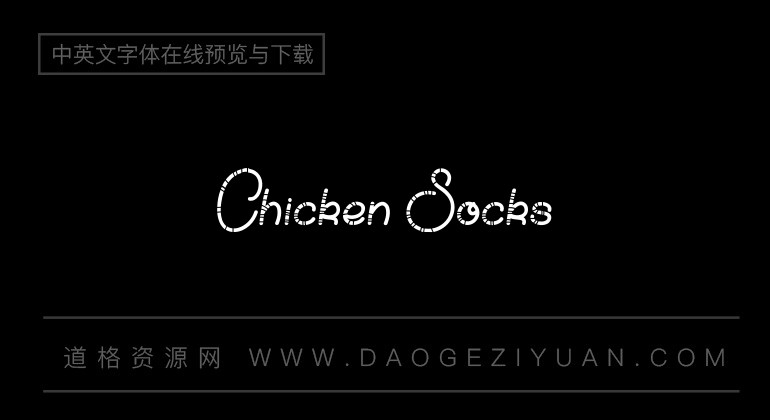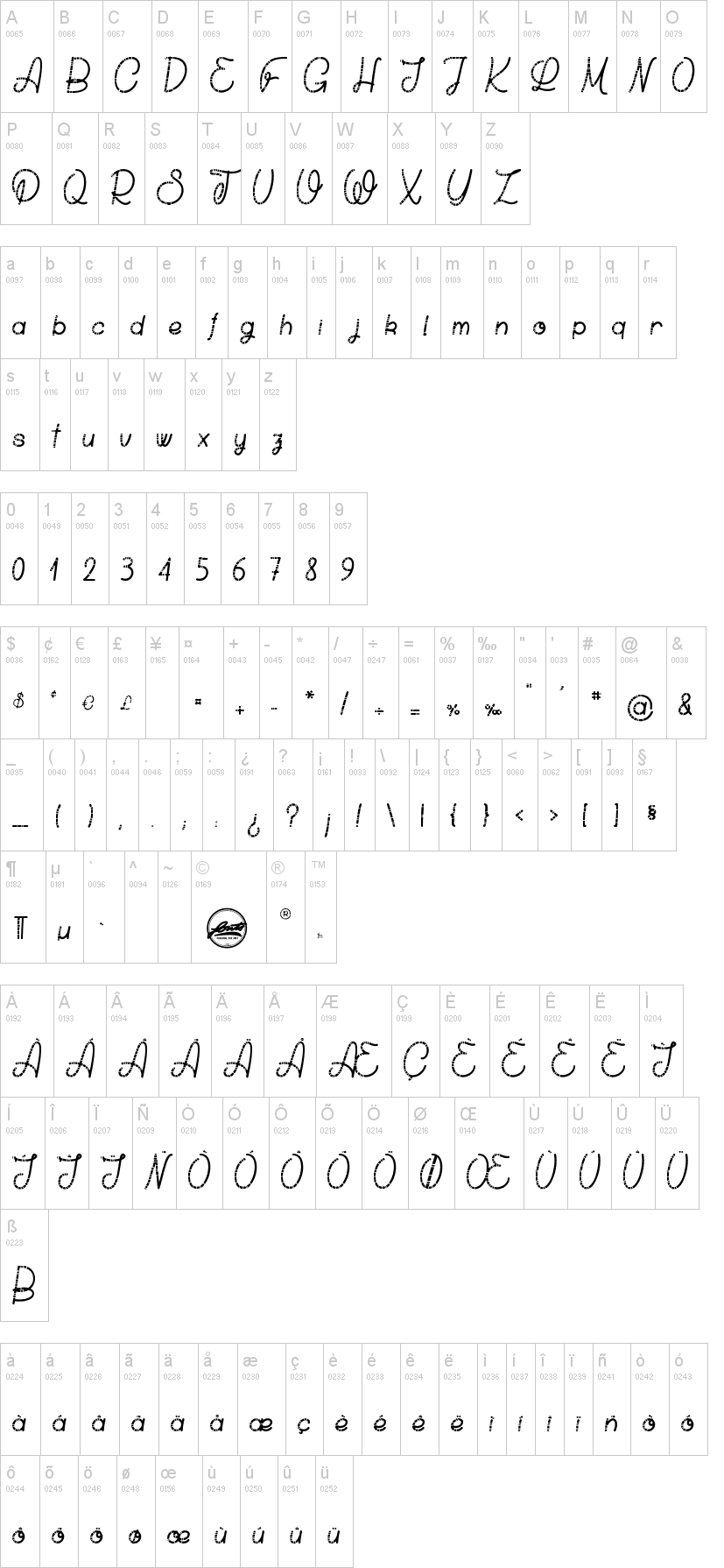
Chicken Socks 字体是一款由英国设计师Liam Smith创作的手写类字体。它的特点是极具特色的萌萌哒的笔画,清新活泼,既可以用于商业设计,也可以用于个人设计,如文字排版、漫画、海报等。它有着独特的风格,能够更好地表达出个性化的设计感。内容介绍
Chicken Socks是一款非常不错的手写艺术字体,具有很好的视觉感,适合于文化类的宣传设计、商业类品牌的广告和产品包装设计以及个性化文字排版等较多场景。